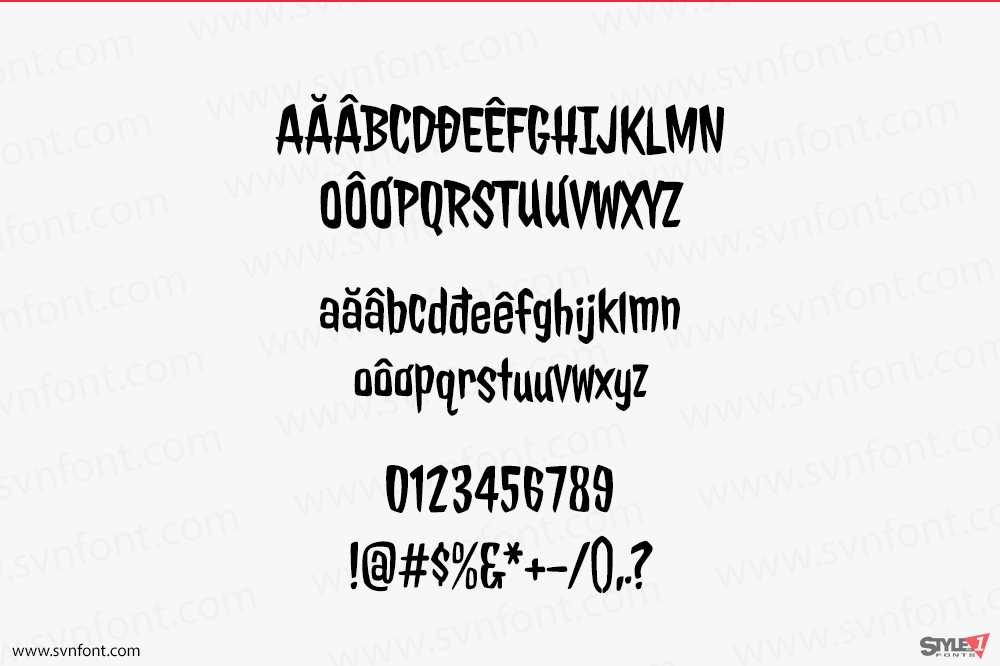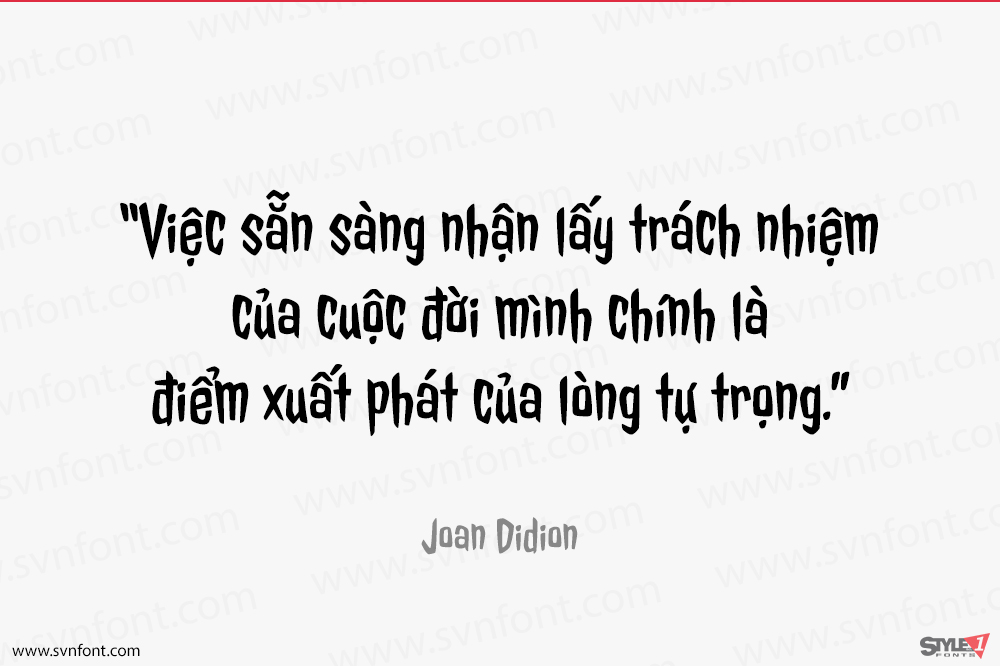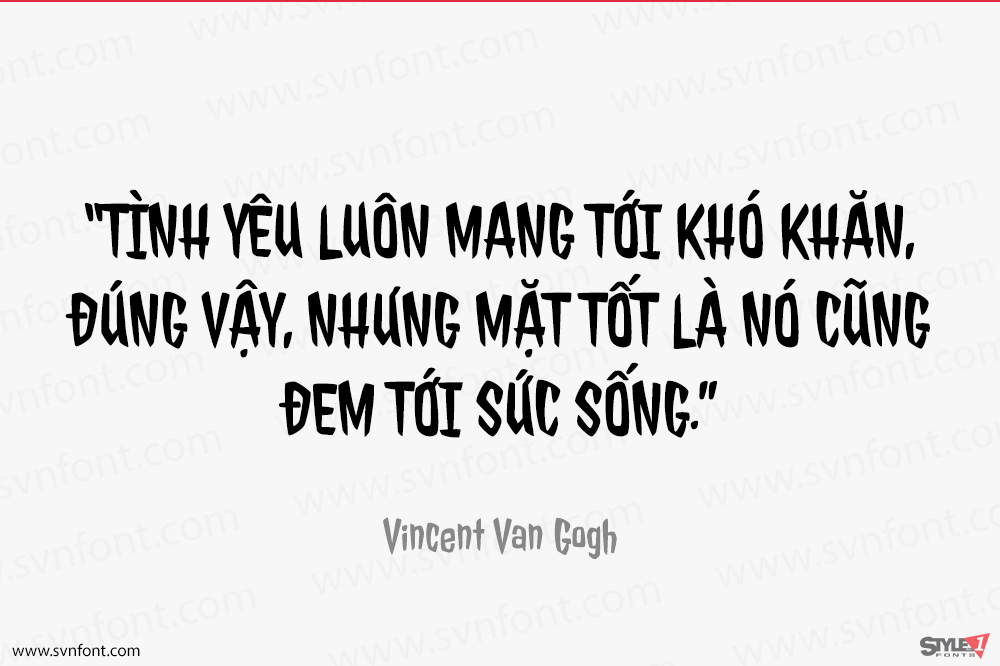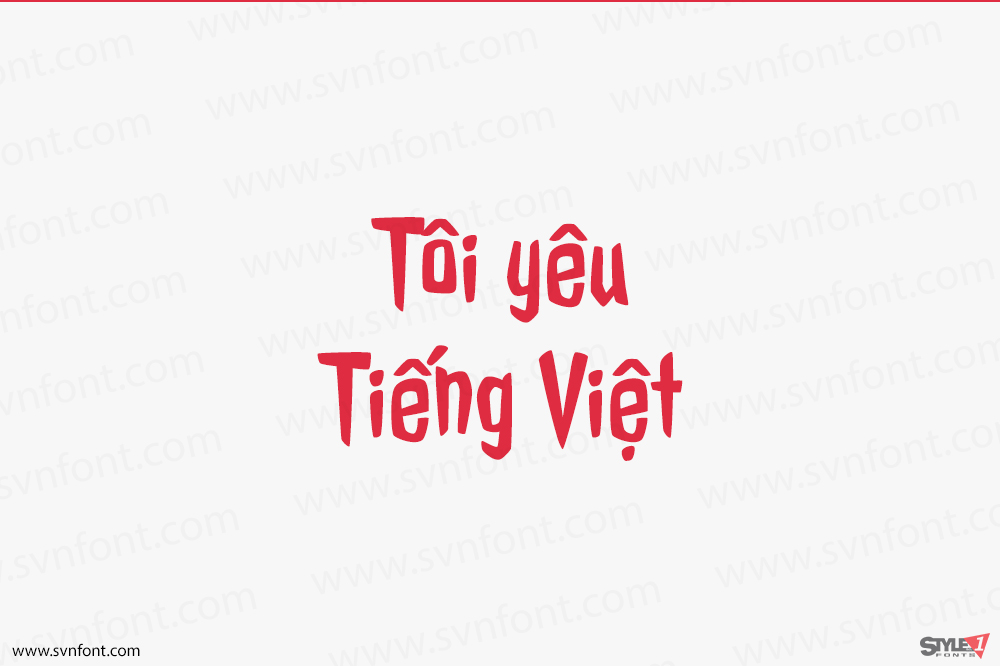
Jolly Lodger là một phông chữ lạ mắt, hoạt hình được thiết kế bởi Font Diner. Phông chữ này được cấp phép theo Giấy phép Phông chữ Mở SIL. Phông chữ này miễn phí cho cả mục đích cá nhân và thương mại, sửa đổi và phân phối.
Nhà thiết kế: Stuart Sandler
Nhà phát hành: Fontdiner